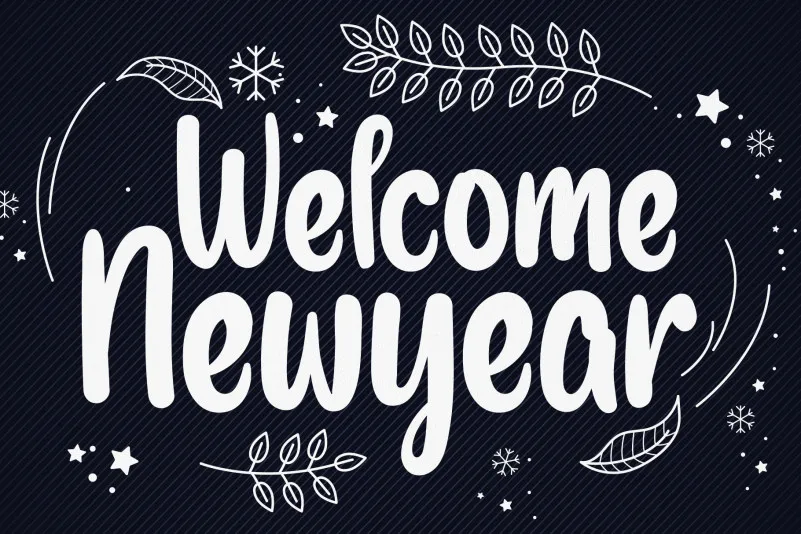
Welcome Newyear Script Font – Download Grátis
A ‘Welcome Newyear Script Font’ é uma fonte script bold e casual que encanta por sua versatilidade. Criada pelo designer andikastudio, ela é perfeita para aqueles desejando um design elegante em suas criações. Suas linhas finas se combinam com traços sóbrios e suas formas fluidas garantem uma aparência única e atraente. Perfeito tanto para assinaturas quanto para subtítulos de apresentações, esta fonte é certamente uma das mais versáteis do mercado. Com sua ‘Welcome Newyear Script Font’, seus designs se destacam ainda mais. Experimente agora!